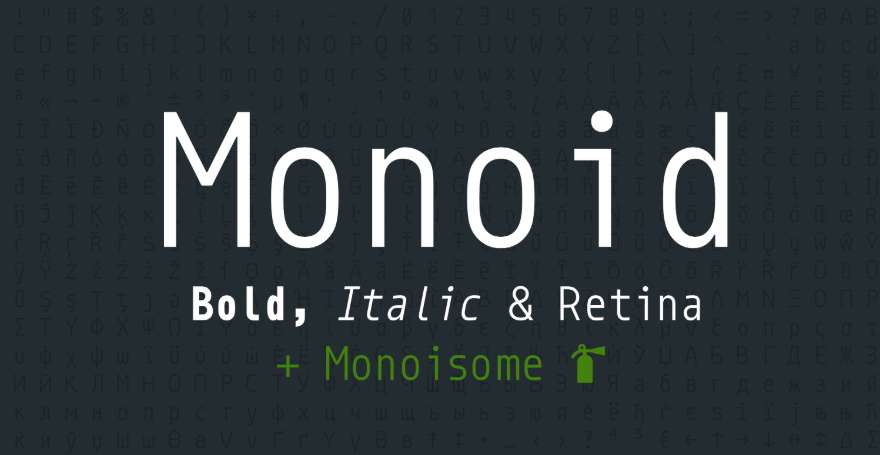
10 meilleures polices de programmation pour vous sauver de la fatigue oculaire
Publié: 2019-04-30La fatigue oculaire est un véritable problème pour les développeurs de logiciels, et la police avec laquelle ils choisissent de travailler joue un grand rôle à cet égard. S'ils choisissent une police qui n'est pas assez bien conçue, la ponctuation ou les caractères peuvent être difficiles à distinguer, ce qui les oblige à se concentrer davantage pour les distinguer, ce qui entraîne des maux de tête, une fatigue oculaire et un taux de productivité généralement inférieur à l'idéal. . Nous ne voulons pas que cela vous arrive, nous allons donc présenter certaines des meilleures polices de programmation qui vous permettront de regarder plus facilement un écran pendant des heures.
1. Saisie
Input est une police de programmation qui a été conçue dès le départ pour faciliter la vie des développeurs de logiciels. Le site lui-même dit que non seulement les caractères, mais aussi la « ponctuation a été conçue pour être grande et claire dans le contexte du code ». Allant plus loin qu'une simple police à espacement fixe (où chaque caractère occupe la même quantité d'espace horizontal), il existe une version sans empattement proportionnellement espacée qui est conçue pour que les codeurs puissent éviter tout type de chevauchement de caractères ou bizarreries dans la taille des caractères. Input est la police d'un programmeur s'il en existe une, et vous vous rendriez service en la vérifiant.
2. Code Fira
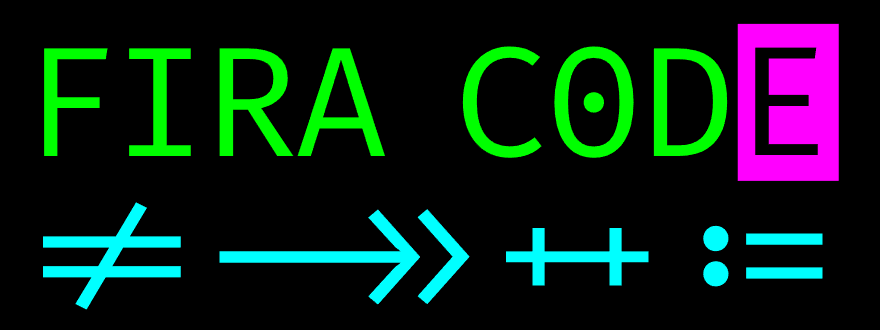
Recommandé par des tonnes de programmeurs en raison de son inclusion de ligatures de codage, Fira Code est une bonne chose. Fira Code est une émanation de la police Fira Mono. Il est développé par Mozilla, vous savez donc qu'il doit être bien conçu et qu'il vaut la peine d'être utilisé. Les programmeurs utilisent un fouillis absolu de symboles et de caractères qui ne sont pas nécessairement des lettres et des chiffres, et Fira Code les corrige automatiquement dans les ligatures égales afin que vous n'ayez plus à discerner les chaînes ASCII, mais plutôt à voir le symbole standard. C'est un code à espacement fixe, et c'est tout simplement magnifique dans n'importe quel éditeur, mais si vous voulez parler de réduction de la fatigue oculaire, ne pas avoir à interpréter la signification des caractères aussi souvent le fera certainement.
3. Les consoles
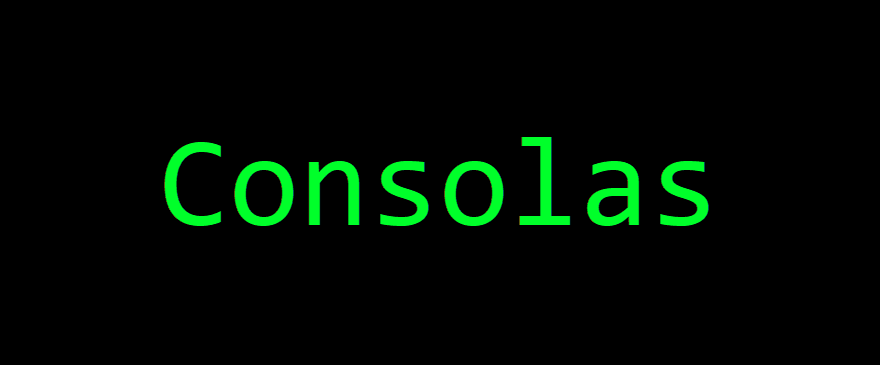
Microsoft s'est lancé dans le jeu des polices de programmation avec Consolas. Incluse dans toutes les installations Windows, Consolas est une police à espacement fixe développée par MS pour être propre, agréable pour les yeux et polyvalente. La documentation MS pour Consolas le dit mieux que nous pouvons:
Tous les caractères ont la même largeur, comme les vieilles machines à écrire, ce qui en fait un bon choix pour la correspondance personnelle et professionnelle. L'affichage amélioré des polices Windows a permis une conception avec des proportions plus proches du texte normal que les polices traditionnelles à espacement fixe comme Courier. Cela permet une lecture plus confortable du texte étendu à l'écran. Les fonctionnalités OpenType incluent des chiffres suspendus ou alignés ; zéros barrés, pointillés et normaux ; et des formes alternatives pour un certain nombre de lettres minuscules. L'apparence du texte peut être adaptée aux goûts personnels en faisant varier le nombre de barres et de vagues.
4. Code source Pro
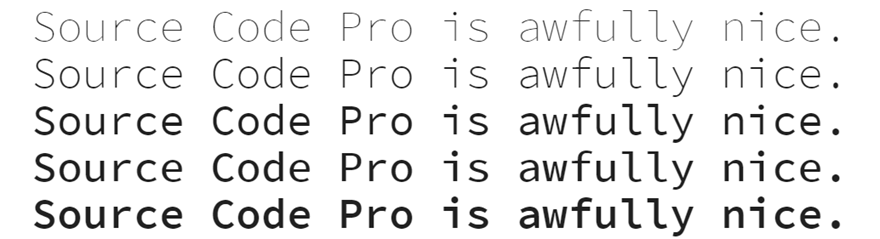
Disponible via Google Fonts, Source Code Pro est une belle police à espacement fixe vers laquelle les codeurs se tournent assez souvent. La variation moyenne (la quatrième en bas dans l'image ci-dessus) est fortement recommandée car, eh bien, elle est moyenne en termes d'épaisseur, ce qui la rend incroyablement facile à lire. Si le nom ne suffisait pas à indiquer, cette famille de polices en particulier a été conçue pour les programmeurs. Il s'agit donc de l'une des meilleures polices de programmation du moment, ce qui ne devrait guère surprendre personne.
5. Monoïde
Crisp, clair et à peu près parfait, Monoid est le rêve d'un programmeur. Alors que la plupart des développeurs sont chargés d'écran ces jours-ci, le fait est qu'il y aura des moments où vous devrez travailler dans un environnement à basse résolution ou avec une fenêtre plus petite qu'idéale. Monoid est là pour vous. Il existe même une intégration Monoid et Font Awesome appelée Monoisome. C'est plutôt chouette. De plus, si vous voulez en savoir plus sur ce que c'est que de travailler sur une police spécialement conçue pour le codage, le créateur écrit beaucoup à ce sujet sur Medium.
6. Ubuntu Mono
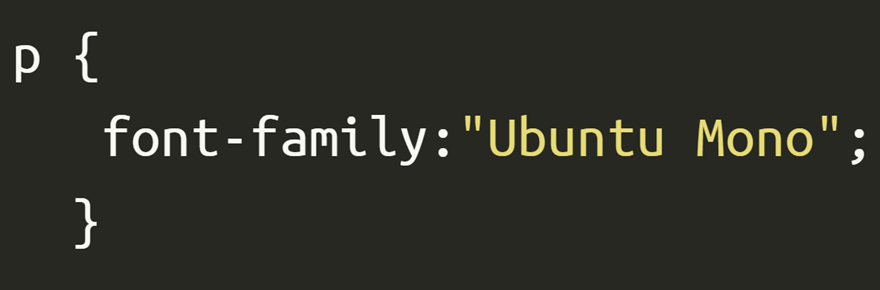
Aucune liste des meilleures polices de programmation ne serait complète sans une police système Linux sur la liste. Ubuntu Mono est un cheval de bataille d'une police qui est à la fois incroyablement lisible, claire et nette sur diverses résolutions, et honnêtement, a l'air vraiment cool. Cela fonctionne bien pour le corps du texte ainsi que pour le codage, et le regarder jour après jour n'entraînera pas de fatigue oculaire ou de maux de tête. Du moins, pas dans notre expérience. De plus, si vous aimez Ubuntu mais devez travailler sous MacOS ou Windows, cela vous donne un petit avant-goût de la maison.
7. Sudo
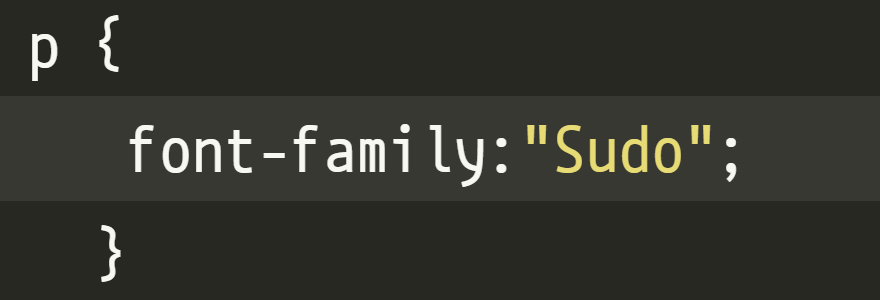
Sudo ressemble beaucoup à Ubuntu Mono, seulement un peu plus écrasé. En fait, c'est une police faite à la main que Jens Kutilek a créée parce qu'ils voulaient une meilleure police de programmation. Dans presque tous les domaines, Sudo réussit en tant que police de programmation. Même si l'espacement est plus compact que certaines familles de polices, les caractères restent parfaitement lisibles car il s'agit toujours d'une police à espacement fixe. Les chiffres et les lettres ont des hauteurs différentes pour une différenciation plus facile, ce qui est incroyablement utile pour le débogage en un coup d'œil.
8. Droïde Sans
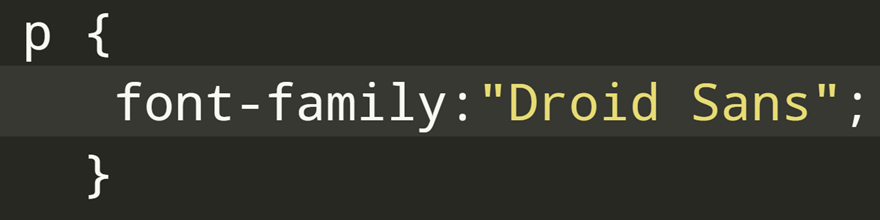
Nous avons toujours eu un faible pour Droid Sans. Depuis sa première inclusion dans Google Fonts, la police propre avait juste l'air technique et comme si elle appartenait à un terminal. Et c'est toujours le cas. La version à espacement fixe de la famille de polices est parfaitement à l'aise dans n'importe quel éditeur de code que vous aimez, et parce qu'elle a été conçue pour la lisibilité sur les écrans mobiles et les navigateurs haute résolution, l'utiliser comme pilote quotidien dans VS Code est dans sa timonerie.
Quelle est votre police de programmation de prédilection pour le développement de logiciels ?